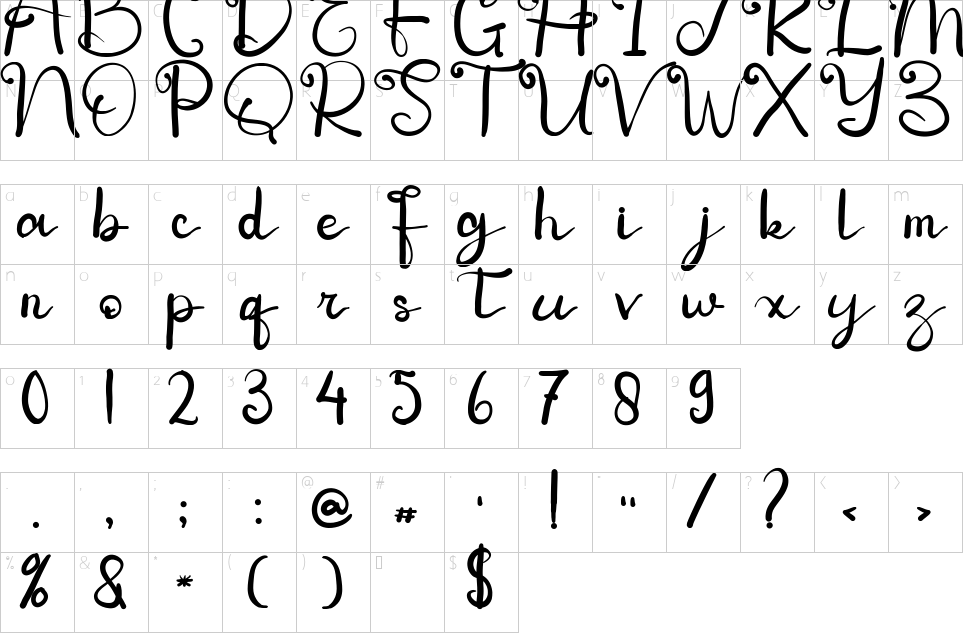
Descubra a delicadeza e a elegância da Agyti Jinny Font, uma fonte grátis perfeita para estilos mais delicados e artísticos. Desenvolvida por Canden Meutuah, essa fonte oferece um contraste suave entre suas linhas e espaçamentos. Seu design suave e elegante torna-a uma escolha agradável para o design editorial, especialmente para títulos e subtítulos, ou para ambientes gráficos que buscam uma harmonia suave e sofisticada. Com seu design cuidadosamente pensado e fácil de ler, Agyti Jinny é uma excelente opção para aqueles buscando uma fonte não apenas gratuita, mas também de alta qualidade. Download Agyti Jinny agora e adicione a sua paleta de fontes de um jeito elegante e moderno.